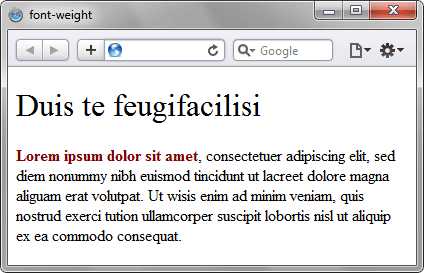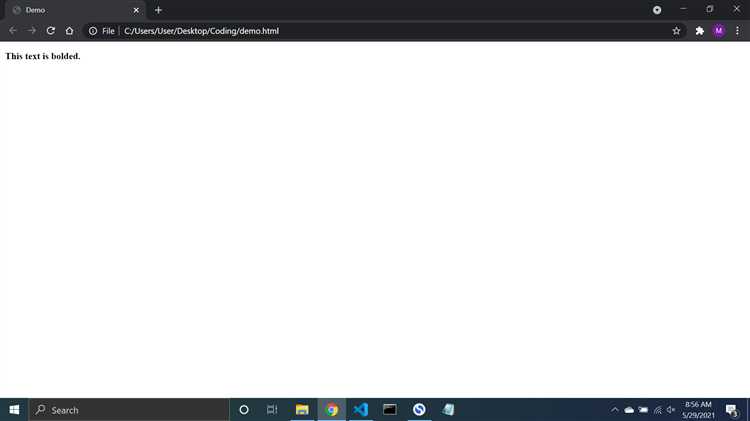
В CSS для изменения начертания текста на жирный используется свойство font-weight. Этот параметр контролирует толщину шрифта, и значение bold является одним из самых распространённых вариантов. Важно помнить, что не все шрифты поддерживают жирное начертание, и в таких случаях браузер может заменить его на максимально доступную толщину.
Чтобы применить жирный шрифт к элементу, достаточно указать font-weight: bold в стилях для нужного тега. Однако стоит учитывать, что свойство может принимать не только строковые значения, но и числовые, например, font-weight: 700, где 700 – это стандартное значение для жирного шрифта.
Помимо стандартного жирного начертания, существуют и другие возможные варианты. Например, некоторые шрифты могут поддерживать дополнительные веса, такие как font-weight: 900, который сделает текст ещё более выраженным. Важно также проверять, как шрифт отображается в разных браузерах и устройствах, чтобы избежать возможных несовпадений.
Как установить жирный шрифт с помощью свойства font-weight
Значение normal
устанавливает обычную толщину шрифта, а bold
делает текст жирным. Числовые значения дают более точный контроль над толщиной. Например, значение 400
соответствует нормальному шрифту, а 700
– жирному. Шкала варьируется от 100 до 900, где 100 – самый тонкий шрифт, а 900 – самый толстый.
Пример использования:
p {
font-weight: bold;
}
Используя числовые значения, можно добиться различных эффектов, подходящих для разных типов контента:
h1 {
font-weight: 900; /* Очень жирный шрифт */
}
p {
font-weight: 300; /* Легкий шрифт */
}
Стоит учитывать, что не все шрифты поддерживают всю шкалу толщины. Если шрифт не поддерживает определенную жирность, браузер автоматически выберет ближайшее доступное значение. Поэтому рекомендуется использовать стандартные шрифты или проверенные веб-шрифты, которые включают необходимые веса.
Чтобы избежать проблемы с несовместимостью, можно использовать свойство font-family
, выбирая шрифт, который точно поддерживает нужные веса:
body {
font-family: 'Roboto', sans-serif;
font-weight: 500;
}
Также важно помнить, что значение font-weight
может применяться не только к текстовым элементам, но и к другим блокам, таким как заголовки, списки или кнопки. Это позволяет создавать текст с различной степенью выделения и контраста.
Разница между значениями normal и bold в CSS
В CSS значения normal
и bold
задают вес шрифта, но их воздействие на визуальное отображение текста зависит от контекста и используемого шрифта. Значение normal
обозначает стандартный вес шрифта, который зависит от его дизайна. Это может быть как обычный, так и более легкий вариант шрифта, если он был специально разработан таким образом. В случае стандартных шрифтов, таких как Arial или Times New Roman, это обычно соответствует нормальному, неприделенному стилю.
Значение bold
применяется для увеличения толщины шрифта, что часто используется для выделения текста. Оно активирует более жирную версию шрифта, если таковая существует. Важно отметить, что не все шрифты имеют ярко выраженную жирную версию, и в таком случае браузер может автоматически сгенерировать утолщение для текста, что может привести к неестественному визуальному восприятию.
Когда используется normal
, это гарантирует, что текст будет отображаться с нормальной толщиной, в то время как bold
делает шрифт более выразительным. Однако на шрифтах с ограниченным набором начертаний, где нет явно выделенной жирной версии, эффект от bold
может быть менее заметным. Если необходимо обеспечить точность в типографике, важно учитывать, какие версии шрифта поддерживаются в конкретном проекте.
Таким образом, выбор между normal
и bold
зависит от желаемого эффекта на внешний вид текста и от наличия соответствующих начертаний шрифта. Правильное применение этих значений помогает улучшить восприятие контента и повысить его читаемость.
Как использовать числовые значения для font-weight
Свойство font-weight
в CSS позволяет управлять толщиной шрифта. Помимо стандартных ключевых значений, таких как normal
и bold
, можно использовать числовые значения для более точной настройки. Эти значения варьируются от 100 до 900 и определяют плотность шрифта.
Числовое значение представляет собой степень насыщенности начертания шрифта, где:
- 100 – наименьшая толщина (ультралёгкий шрифт).
- 400 – стандартная толщина шрифта (обычно используется для обычного текста, аналог
normal
). - 700 – жирное начертание (аналог
bold
). - 900 – максимально толстый шрифт.
Для использования числовых значений необходимо указать их непосредственно в свойстве font-weight
:
p {
font-weight: 300;
}
Рекомендуется использовать диапазоны от 100 до 900, при этом шаг между значениями обычно составляет 100 (например, 100, 200, 300, 400 и так далее). Некоторые шрифты могут поддерживать не все значения, в таких случаях CSS применяет ближайшее доступное.
Вопрос-ответ:
Есть ли какие-то особенности при применении жирного шрифта для разных шрифтов?
Да, некоторые шрифты могут не поддерживать разные степени жирности. В этом случае, если шрифт не имеет жирной версии, браузер будет пытаться сделать текст жирным с помощью алгоритмов рендеринга, что может привести к не совсем точному отображению. Чтобы избежать этого, рекомендуется использовать шрифты, которые имеют несколько вариантов веса, например, Google Fonts, где можно выбрать нужный вес шрифта при подключении.